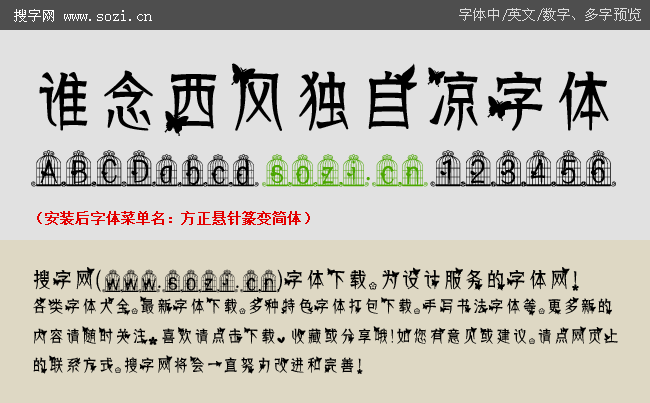
誰念西風獨自涼字體
搜字網(wǎng)給大家提供一款誰念西風獨自涼字體手機中文字體下載。這款手機字體是在方正懸針篆變簡體筆畫間插入了卡通圖案。方正懸針篆變字體意在保留篆書韻味,同時將隸書與楷書筆畫特征熔于一爐,實為三種書體的統(tǒng)一。將傳統(tǒng)書法藝術與現(xiàn)代形式語匯融合,追求裝飾性及藝術美感,端莊秀美、開張疏朗,雍容大氣、復古卻易讀。加入了卡通圖案后又增添了趣味性,特別適合喜歡手機字體個性一些的朋友在手機上安裝使用。